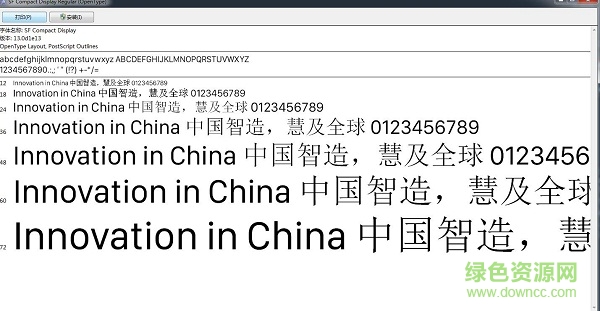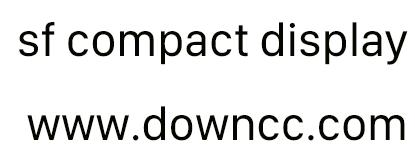
sf compact display字體是蘋果官方為watch os打造的一款無襯線字體,清晰易讀,字體包收錄了粗體、常規(guī)體、細體三款,可以完全滿足用戶的使用需求,歡迎需要的朋友前來下載!
SF Compact這個字體目前專門為 Watch OS 設計,該字體最明顯的差異就是字碗(Bowl)的設計,Compact的更加平直,顯的瘦長,手表的界面非常小,通過增加字體間間距可以提高字體的閱讀性。